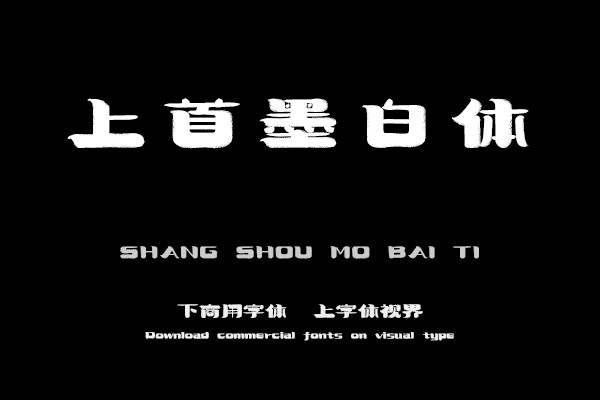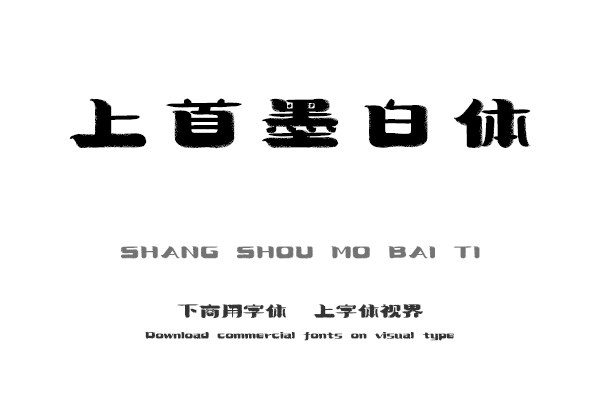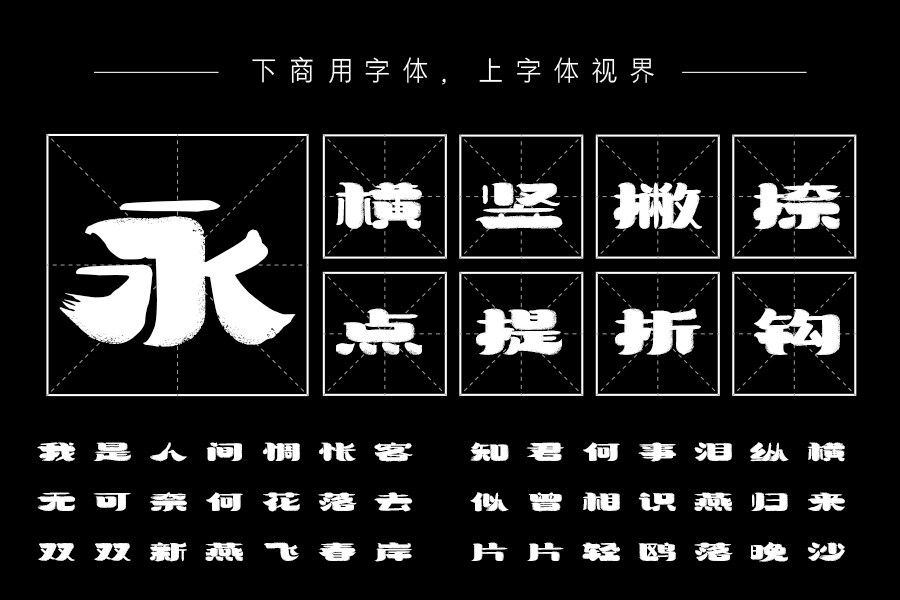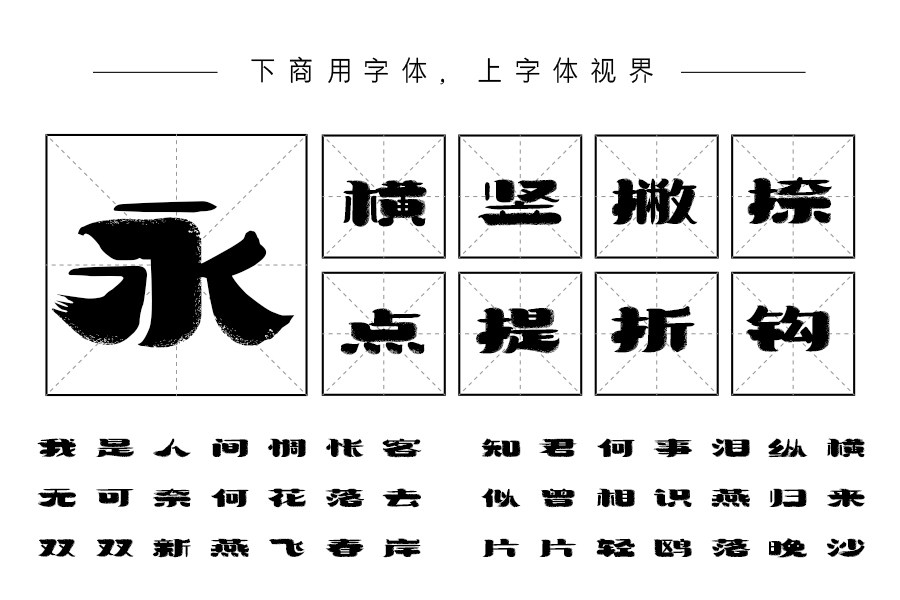
上首墨白体,该字体的笔画较为工整,整套字体较为扁平、圆钝,粗细对比明显,笔画边上的粒子效果的留白,有一种历尽风霜经过漫长岁月冲刷的感觉,赋予了该套字一种独特的历......购买须知:“下载服务费”与“字体VIP”所获得字体 仅用于个人非商用, 商用请联系付费授权。本字体为电脑用字,手机没有root权限不支持直接手机换字(手机如何root,请自行百度搜索教程)。购买前请先 了解清楚后再付款 ,字体为虚拟产品无法回收 一旦购买不支持退款。